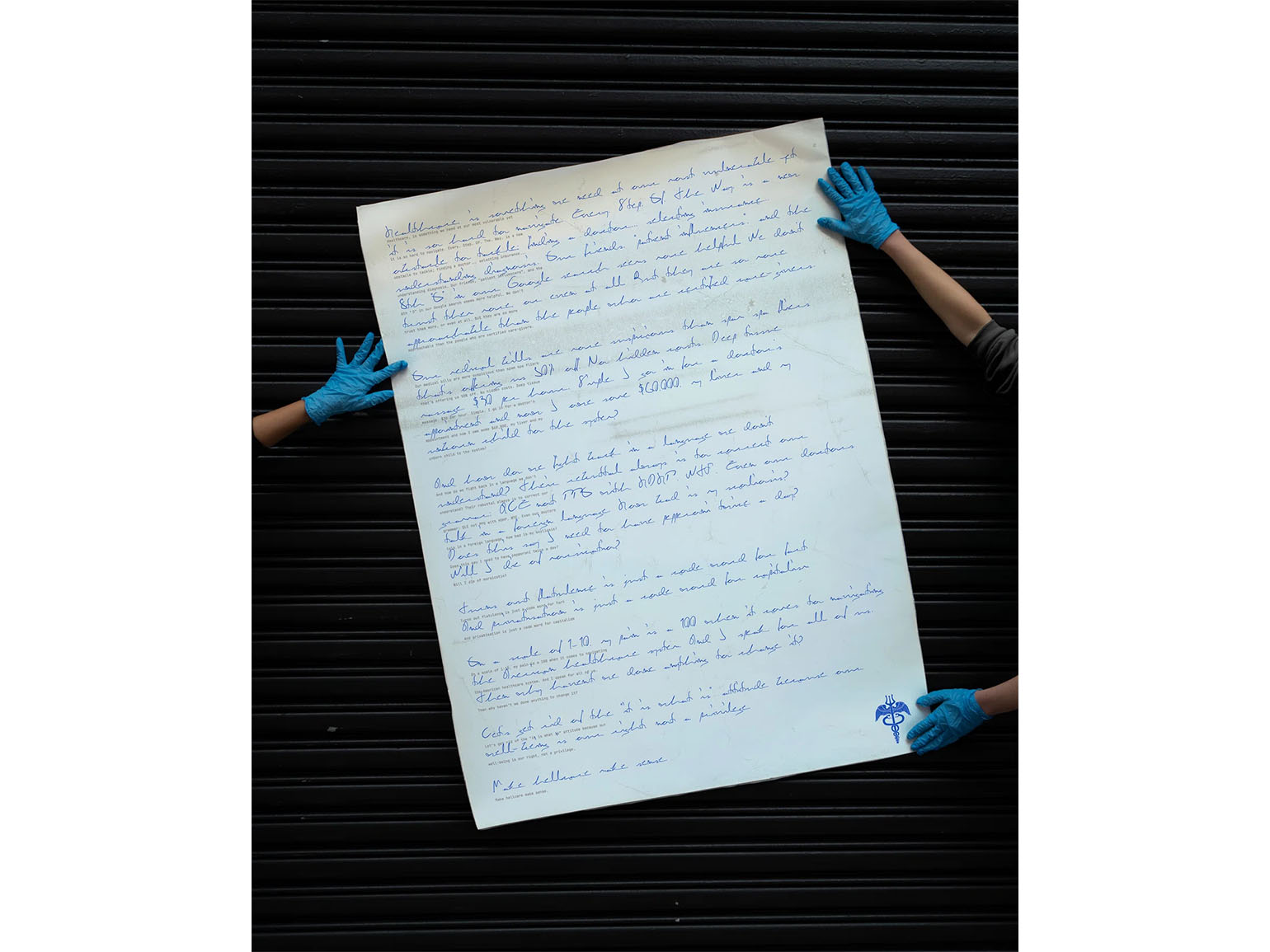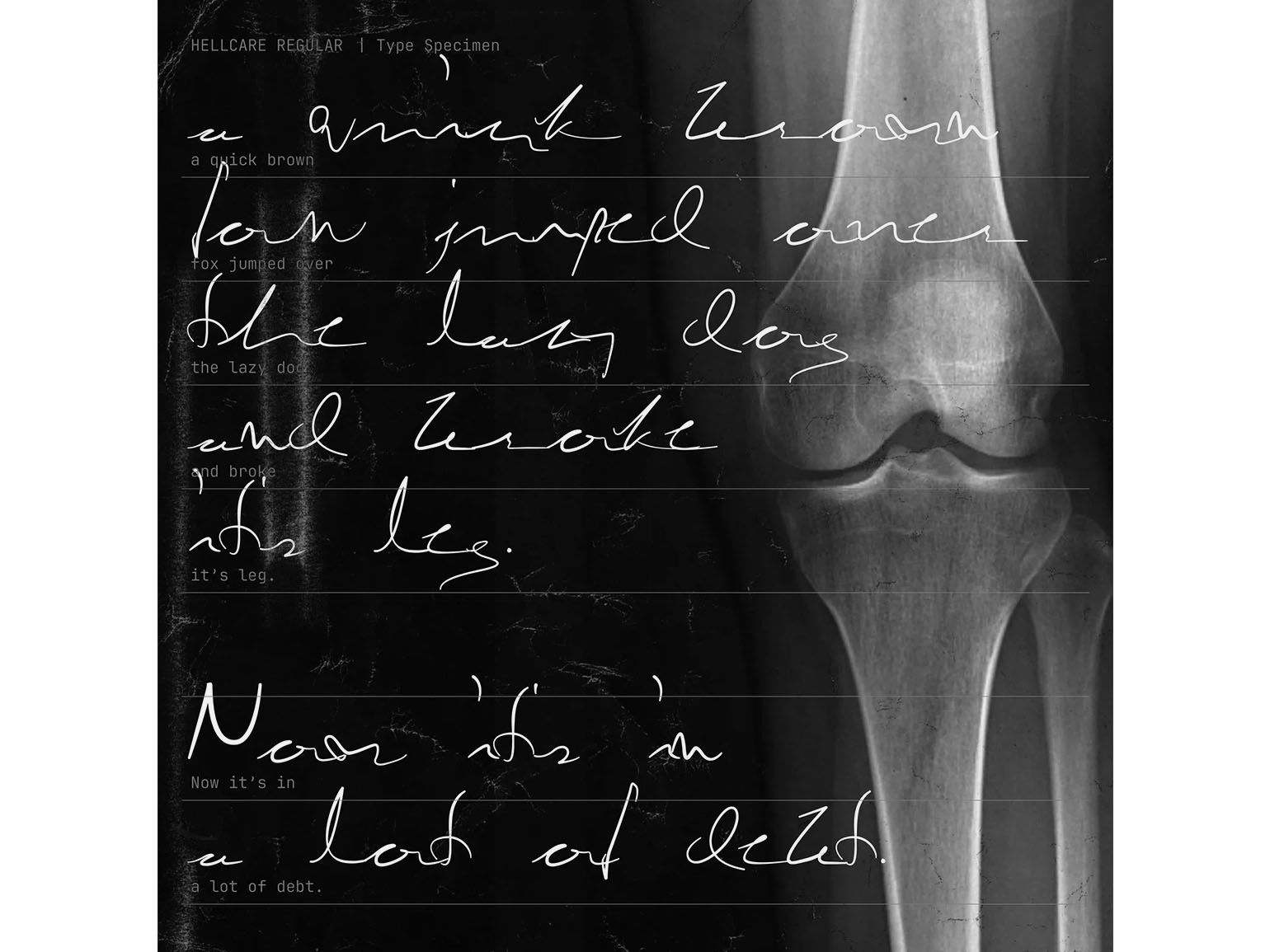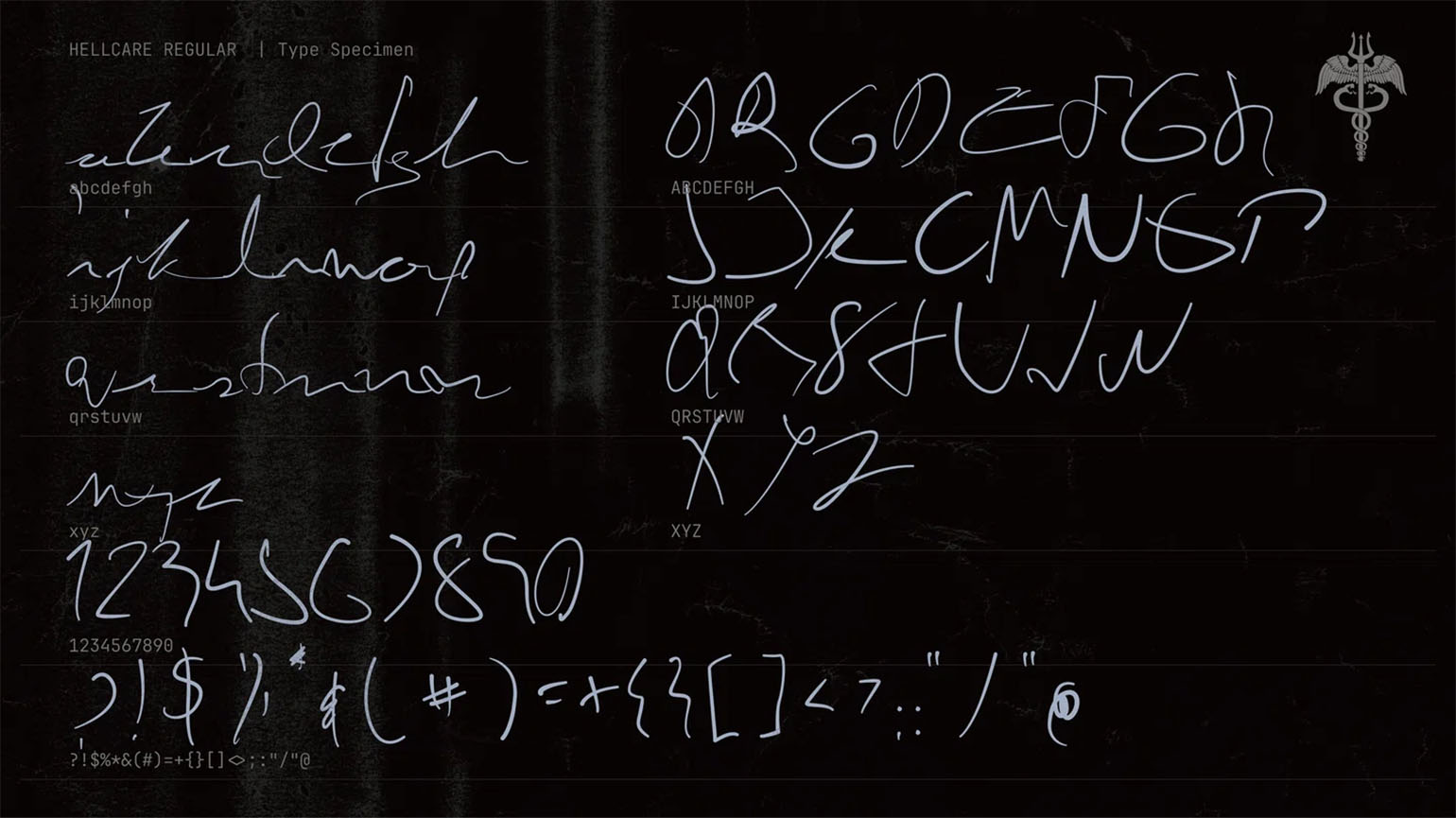
Дизайнеры создали шрифт, имитирующий неразборчивый почерк врачей
Это проект, показывающий одну из проблем американской медицины.
Арт-директора нью-йоркского агентства Wieden+Kennedy Паркер Джонс и Раджшри Сараф разработали шрифт Hellcare Regular. При его создании авторы вдохновились знаменитым «врачебным почерком», который почти невозможно разобрать. Проект стал высказыванием о сложности и непрозрачности американской системы здравоохранения: неправильно прочитанная справка от врача в этой стране может привести к финансовому краху.
Идея появилась во время совместной работы дизайнеров. В тот период отец Паркер Джонс проходил лечение от рака четвёртой стадии, и ей приходилось постоянно разбираться в медицинских документах, рецептах и заключениях врачей, что стало для неё отдельным стрессом. Тогда дизайнеры решили превратить это ощущение в визуальный проект.
Чтобы создать шрифт, они изучали реальные медицинские записи и анализировали, как буквы «слипаются» друг с другом и теряют читаемость. Авторы экспериментировали с максимально быстрым письмом, стараясь добиться эффекта полной неразборчивости. При этом перед ними стояла парадоксальная задача: сохранить в хаотичных символах структуру настоящего алфавита.
«Самым сложным было найти баланс: каждая буква должна была выглядеть поспешной и хаотичной, но при этом работать как часть единой системы», — объясняет Джонс.
Название Hellcare отсылает к «адскому» опыту взаимодействия с американской медициной. Авторы подчёркивают, что проект не направлен против врачей. Для них это способ показать, насколько общество привыкло считать нормой вещи, которые по факту остаются недоступными и непонятными для пациентов.